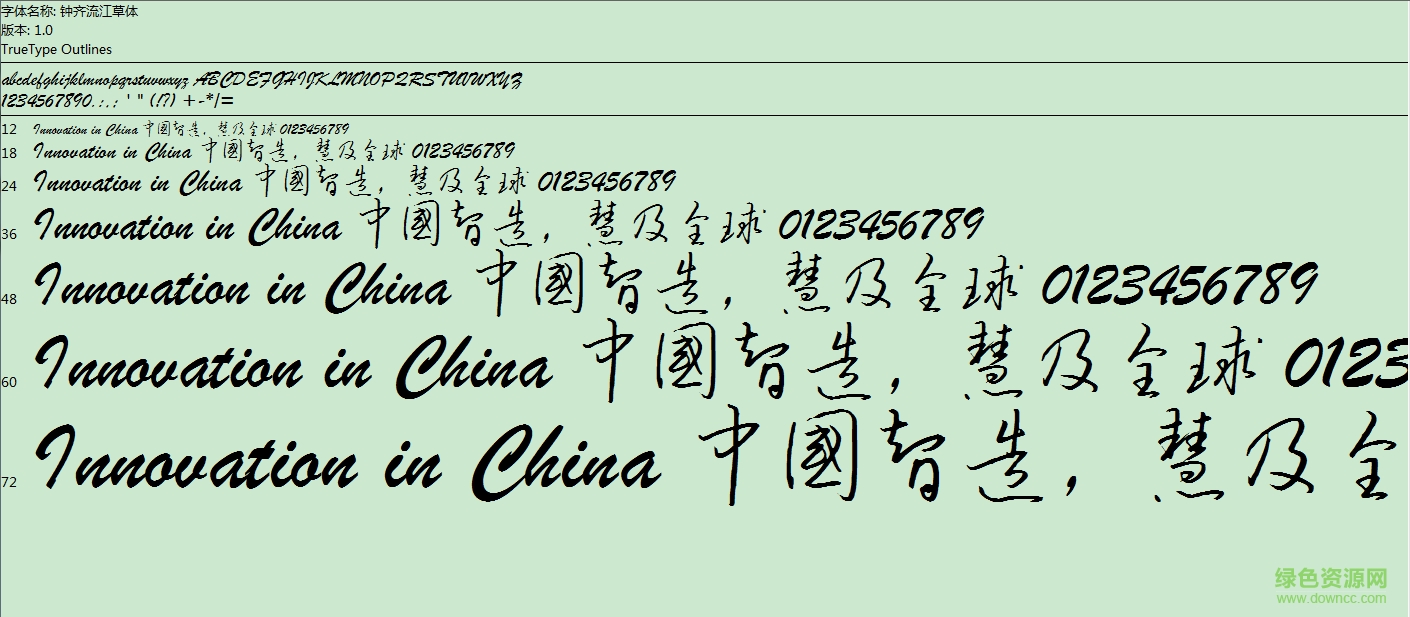
鐘齊流江毛筆草體是一款毛筆書法類字體,這款字體瀟灑飄逸、行云流水,受到很多書法愛好著的青睞和喜愛,感興趣的朋友歡迎來綠色資源網(wǎng)下載體驗(yàn)!
鐘齊流江毛筆草體是一款應(yīng)用于毛筆書法設(shè)計(jì)方面的中文字體,字形瀟灑飄逸,可用于印刷包裝、平面設(shè)計(jì)、廣告創(chuàng)意、毛筆書法等行業(yè)領(lǐng)域。
流江,生于中州河南。自幼熱愛書法,喜歡寫字,但并不理想。每當(dāng)游歷于歷代書法之廊,“隸篆楷行草”竟有些茫然而不知所措。然更鐘情于“行草”,尤以草書最愛。但也深深地知道,在浩瀚的書法海洋之中,在眾多的大家、老師面前,自己充其量只不過算是一個(gè)書法愛好者而已。幾十年來,當(dāng)過農(nóng)民、工人、教師、機(jī)關(guān)干部,從事過文字工作、行政工作和黨群工作,現(xiàn)供職于中國(guó)石油管道公司,教授級(jí)高級(jí)職稱。